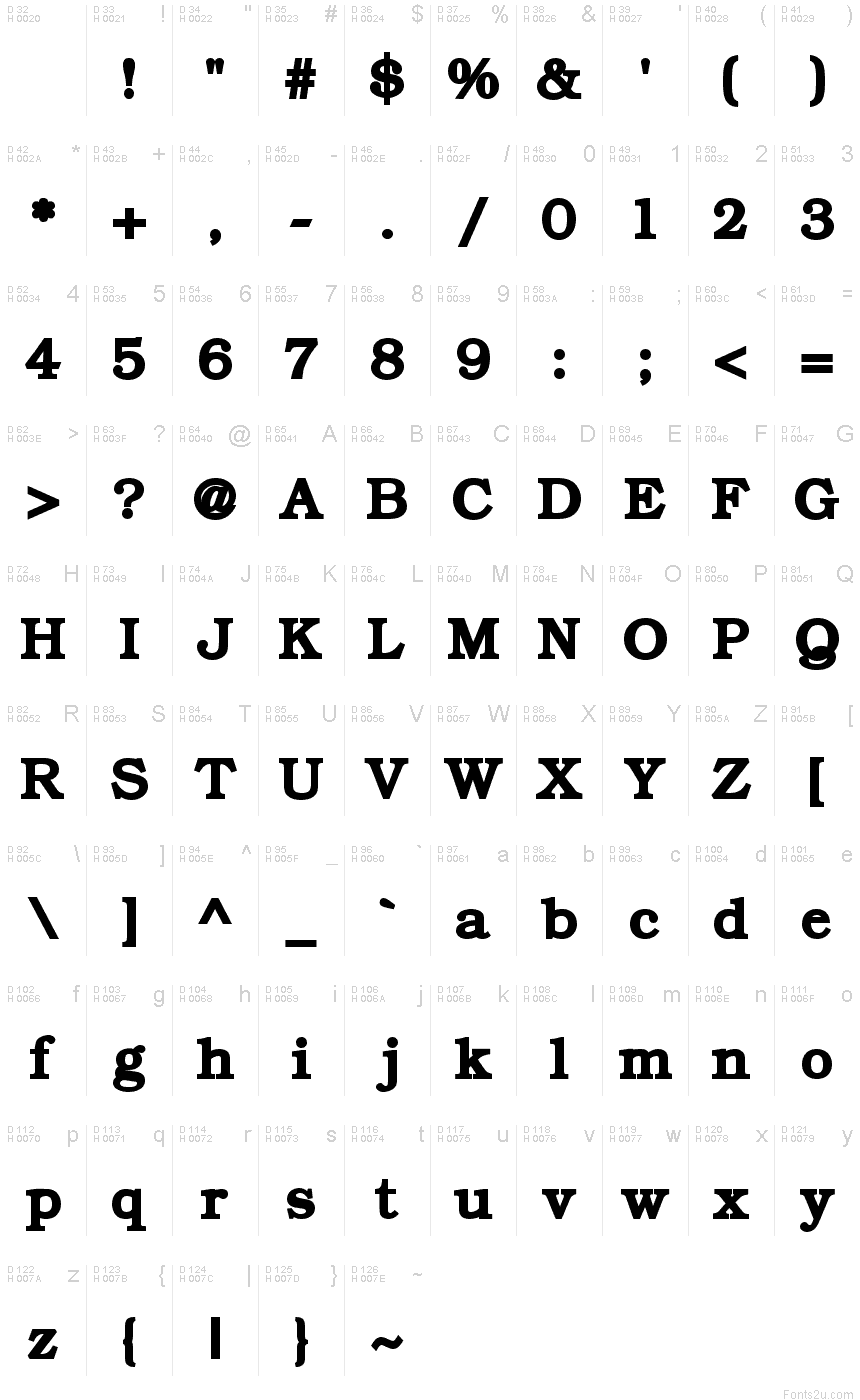
ER Bukinist 866 Bold
ER Bukinist 866 Bold od Gavina Helfa wnosi do rodziny ER Bukinist 866 solidny, nasycony tuszem charakter, z wyrazistymi szeryfami i pewnymi, krągłymi liniami, które kojarzą się z grzbietem starej książki. To darmowy, pogrubiony krój szeryfowy, stworzony z myślą o sytuacjach, w których potrzeba autorytetu bez zbędnych ozdobników.
Wypróbuj ER Bukinist 866 Bold na okładkach książek, logotypach księgarni, tytułach redakcyjnych, opakowaniach w stylu heritage, plakatach wydarzeń, cytatach i nagłówkach rozdziałów. Zapewnij mu odpowiednie marginesy i zestaw z wyrazistym, neutralnym bezszeryfowym krojem w tekście głównym, aby ten darmowy font zachował swoją wyrazistość i czytelność.